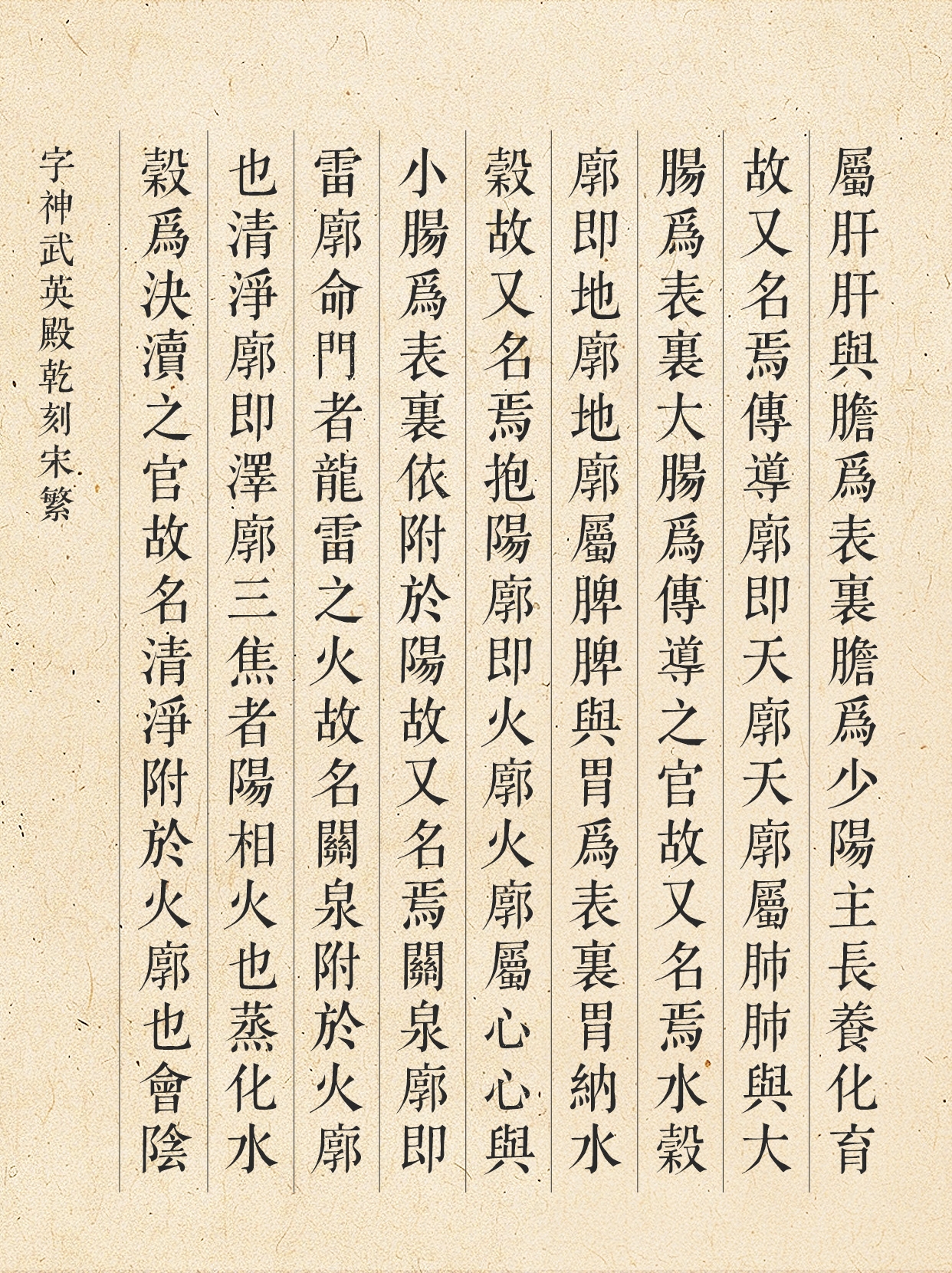
“字神武英殿乾刻宋家族”以《御纂医宗金鉴》武英殿刻本为蓝本,兼具宫廷官刻的规整感与医学典籍的严谨质感。遵循 “字形方正、横平竖直” 的框架,字势舒展均匀,方正端稳,尽显官刻典籍的法度严谨;横细竖粗对比清晰,竖画起笔厚重、收笔利落,自带 “刀刻锋芒” 的工整质感。适合应用于文化宣传、学术出版、艺术展览、非遗文创等场景。